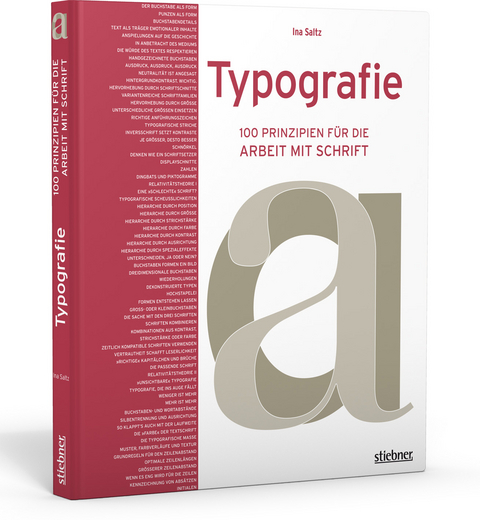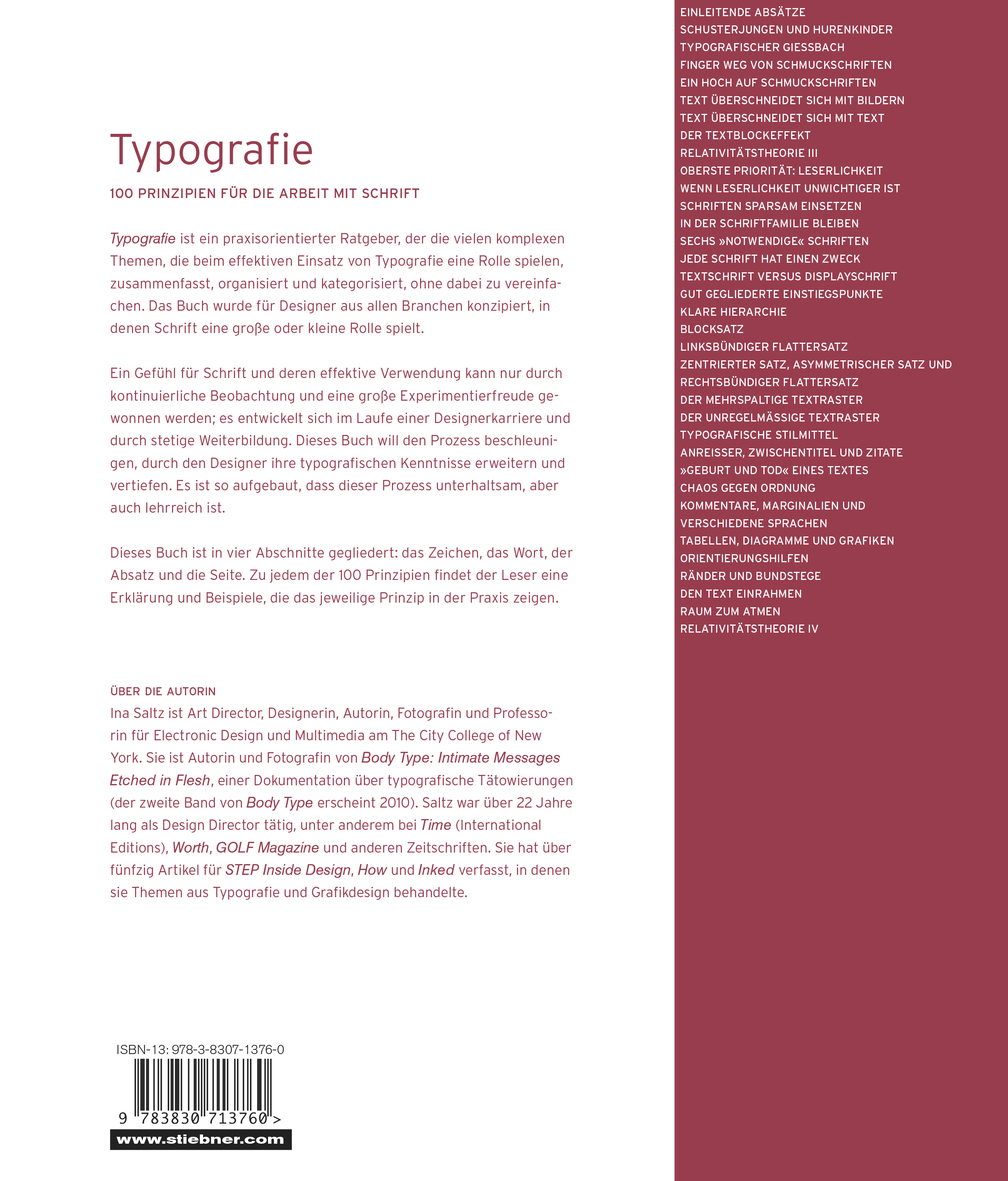
Typografie - 100 Prinzipien für die Arbeit mit Schrift
Schrift transportiert nicht nur Inhalt - sie ist oftmals Bestandteil von ihm: Typografie kann gliedern und gewichten, sie kann sich vornehm zurückhalten oder aber laut im Vordergrund stehen. Niemals gibt es nur die eine 'richtige'für ein Designkonzept, jedoch verändert sich je nach Schriftwahl der gestalterische Ausdruck und damit auch die Aussage. Ina Saltz beleuchtet an unzähligen Beispielen, was Schrift leisten kann und muss: Einhundert Prinzipien hat die Autorin herausgearbeitet, von denen sich der Designer leiten lassen kann. Der Band baut sich äußerst spannend, lehrreich sowie verständlich auf und ist somit ein unverzichtbarer, komplexer und lebendiger Ratgeber zu allen grundlegenden Typografiefragen.